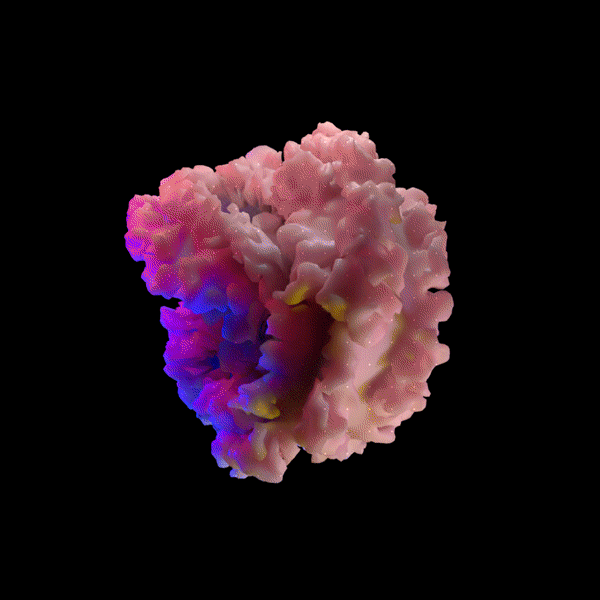
Designer se inspira em corais para criar tipografias fantásticas
Oliver Latta é um designer com grande experiência tipográfica, e recentemente criou uma série de tipografia inspirada em recifes de corais.
Para ele os corais são repletos de vida e diversos em todo o mundo e toda essa diversidade o fez se inspirar na criação de tipografias criativas e totalmente divertidas.
Veja abaixo o resultado dessa incrível série.